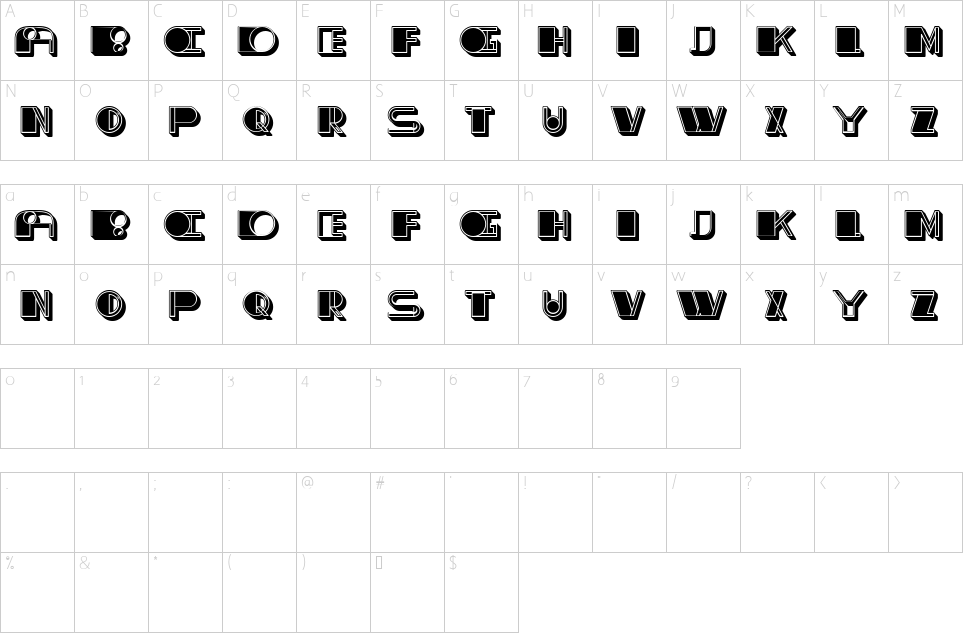
A fonte Assignation é uma elegante e versátil opção para designers gráficos que buscam um estilo clean e moderno. Desenvolvida pelo designer Vladimir Nikolic, esta fonte oferece uma ampla gama de opções, adequada para diversos projetos, desde logotipos e materiais de mídia social até artigos de blog e anúncios online. Com seu design limpo e sofisticado, a Assignation não apenas combina perfeitamente com outros tipos de fontes, mas também permite que os designers criem layouts de texto de alta qualidade e profissionalismo. Se você está procurando por uma fonte de qualidade que pode ser usada tanto em projetos pessoais quanto profissionais, o Assignation pode ser uma escolha ótima. Descarregada pelo número recorde de 141 vezes, a Assignation continua sendo uma fonte de grande valor para quem busca estilos criativos e modernos para seus projetos digitais.